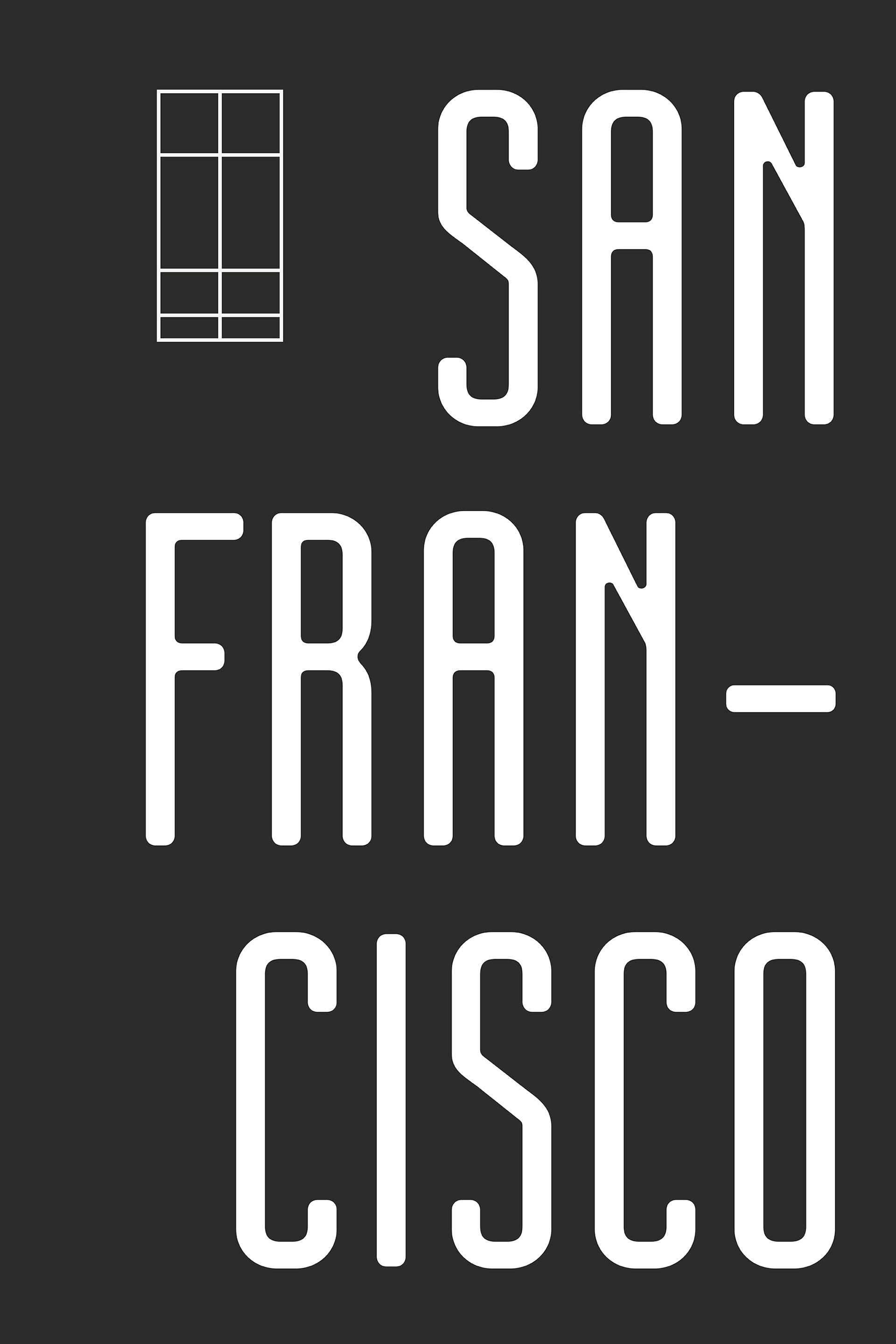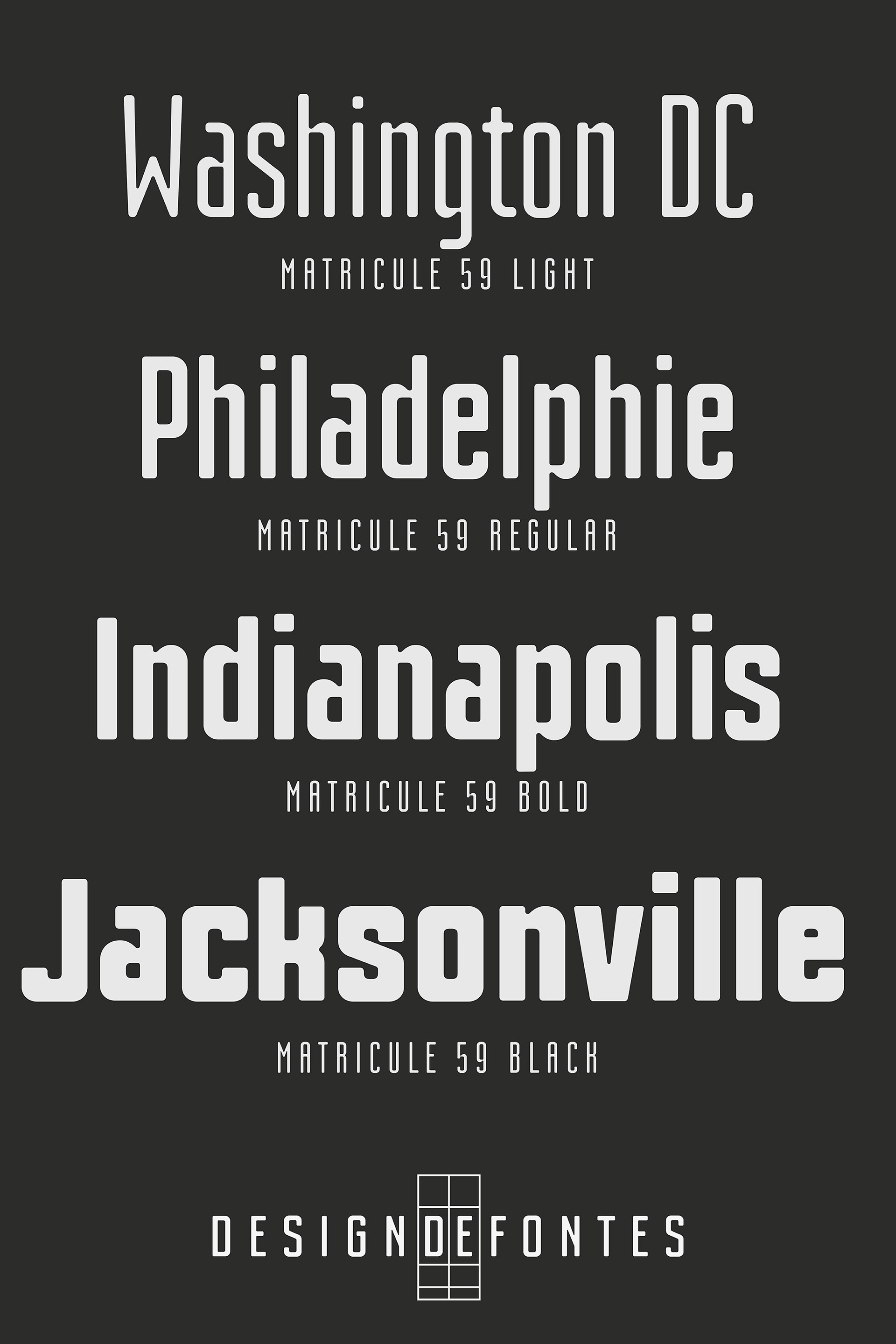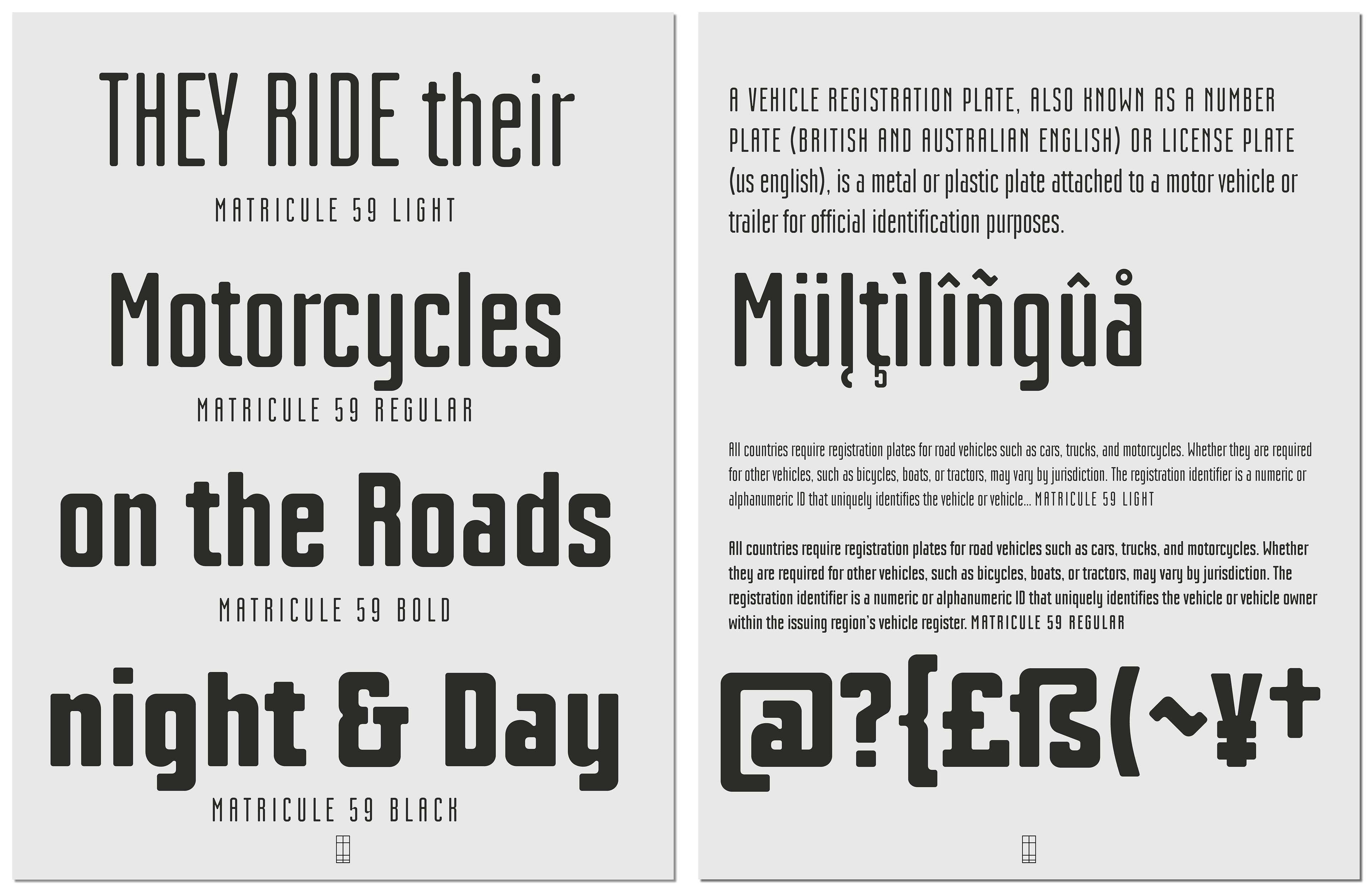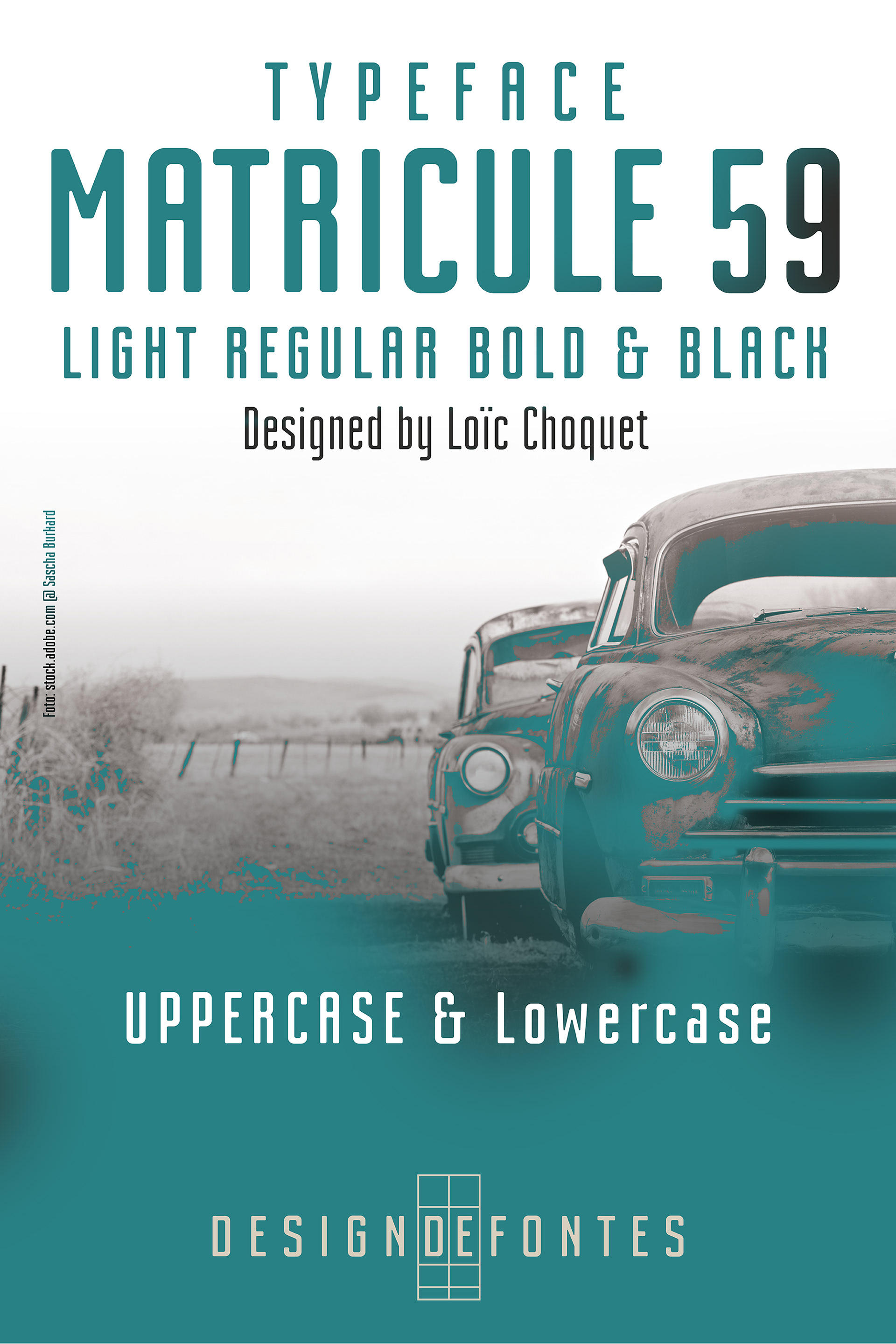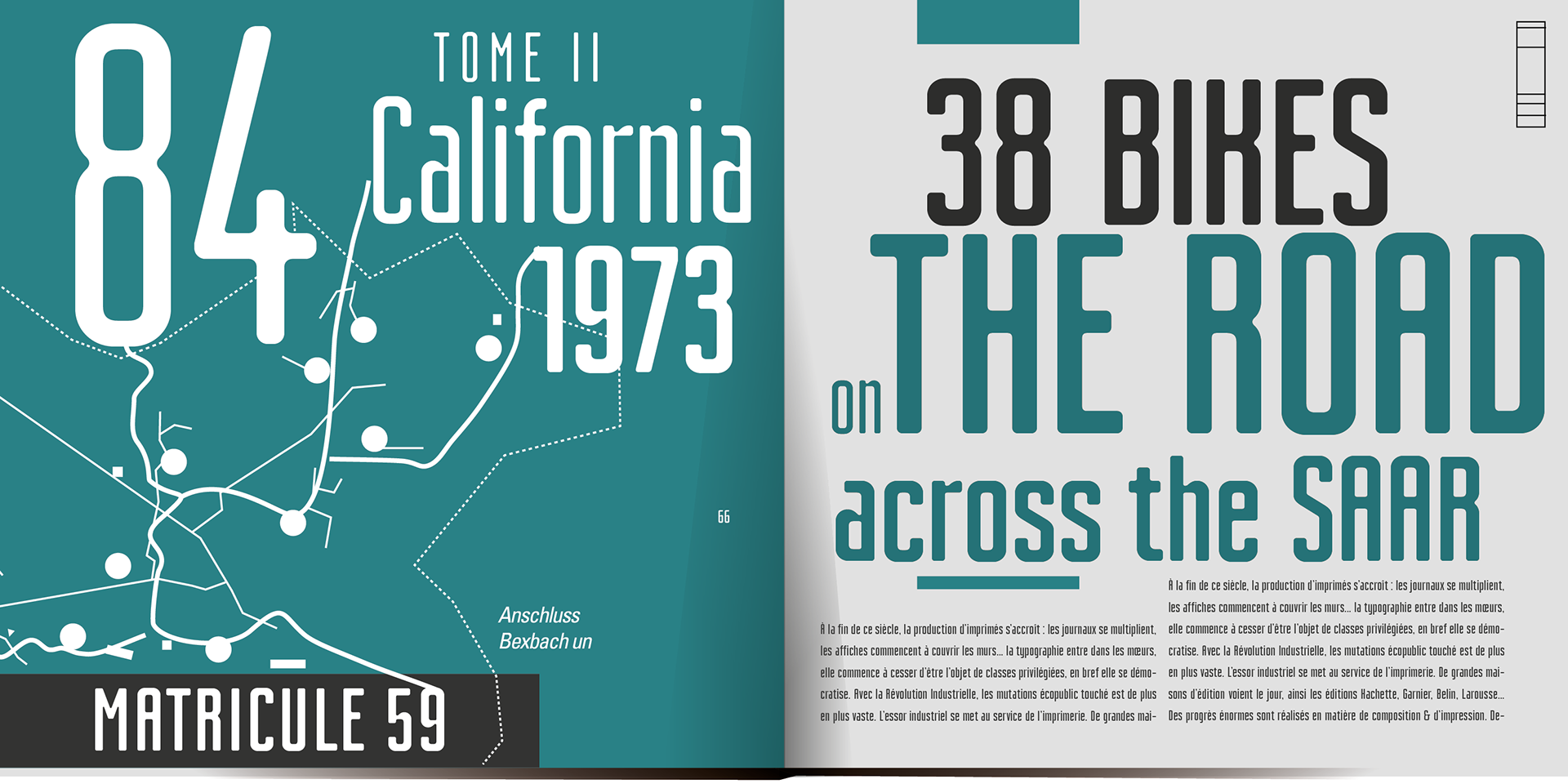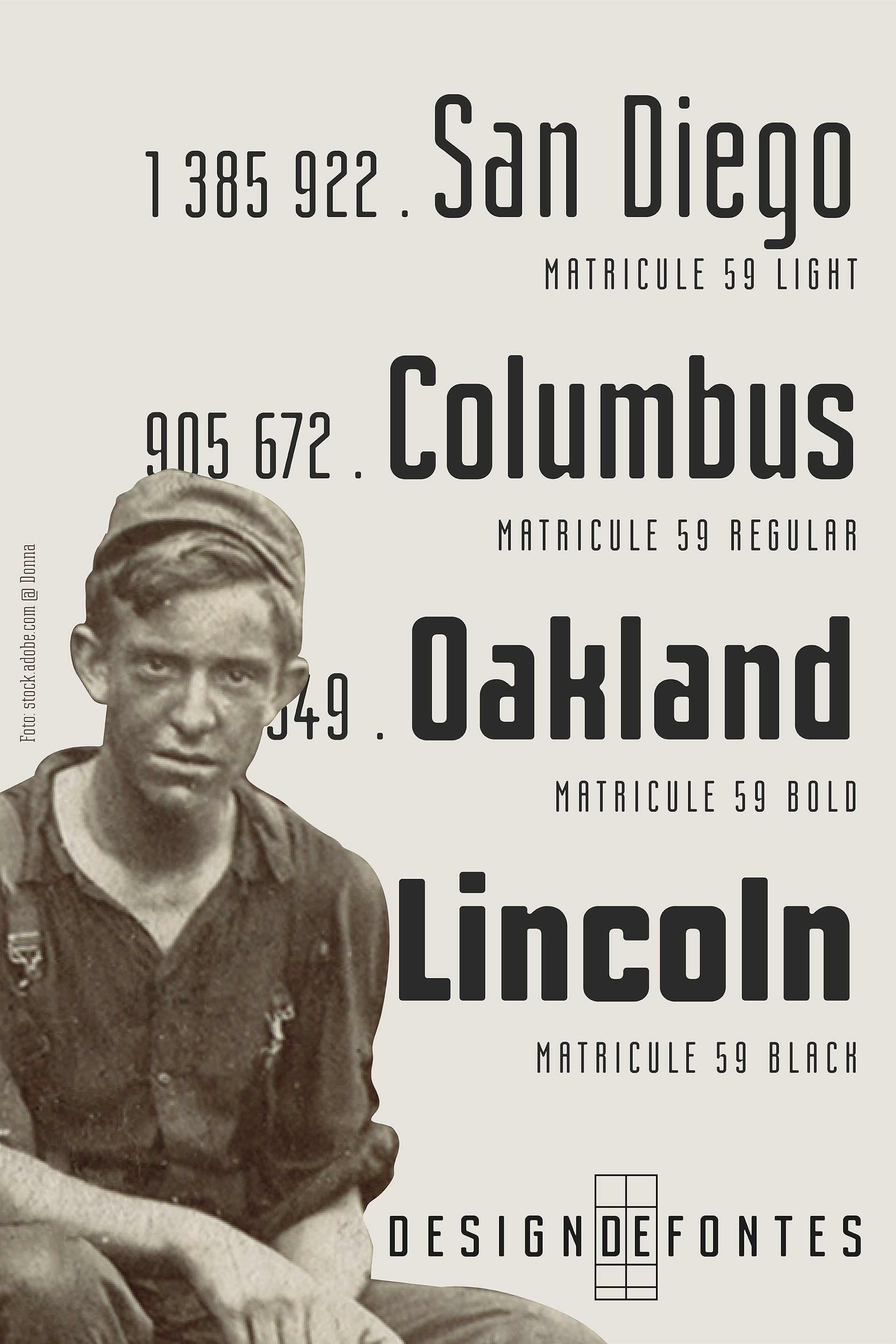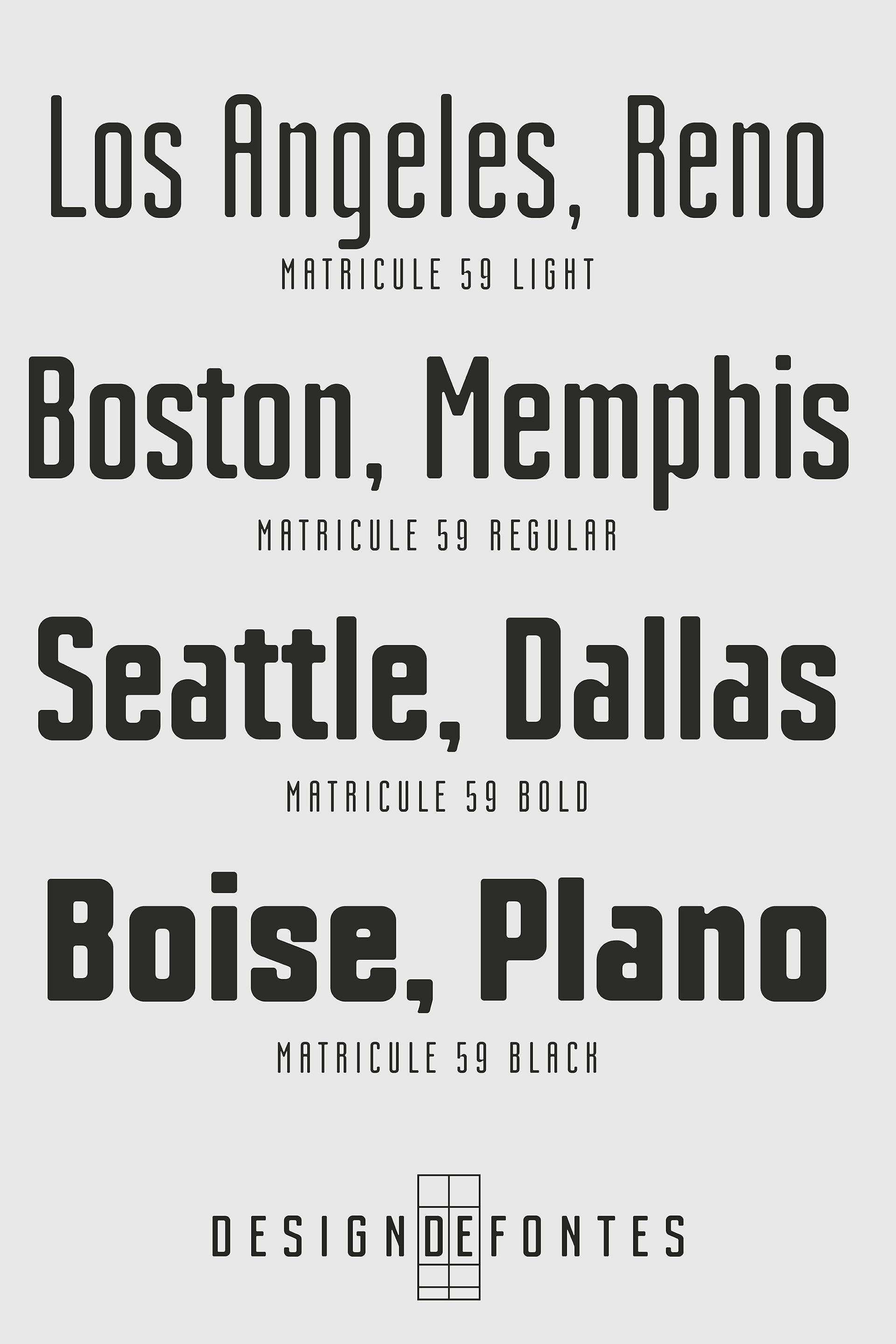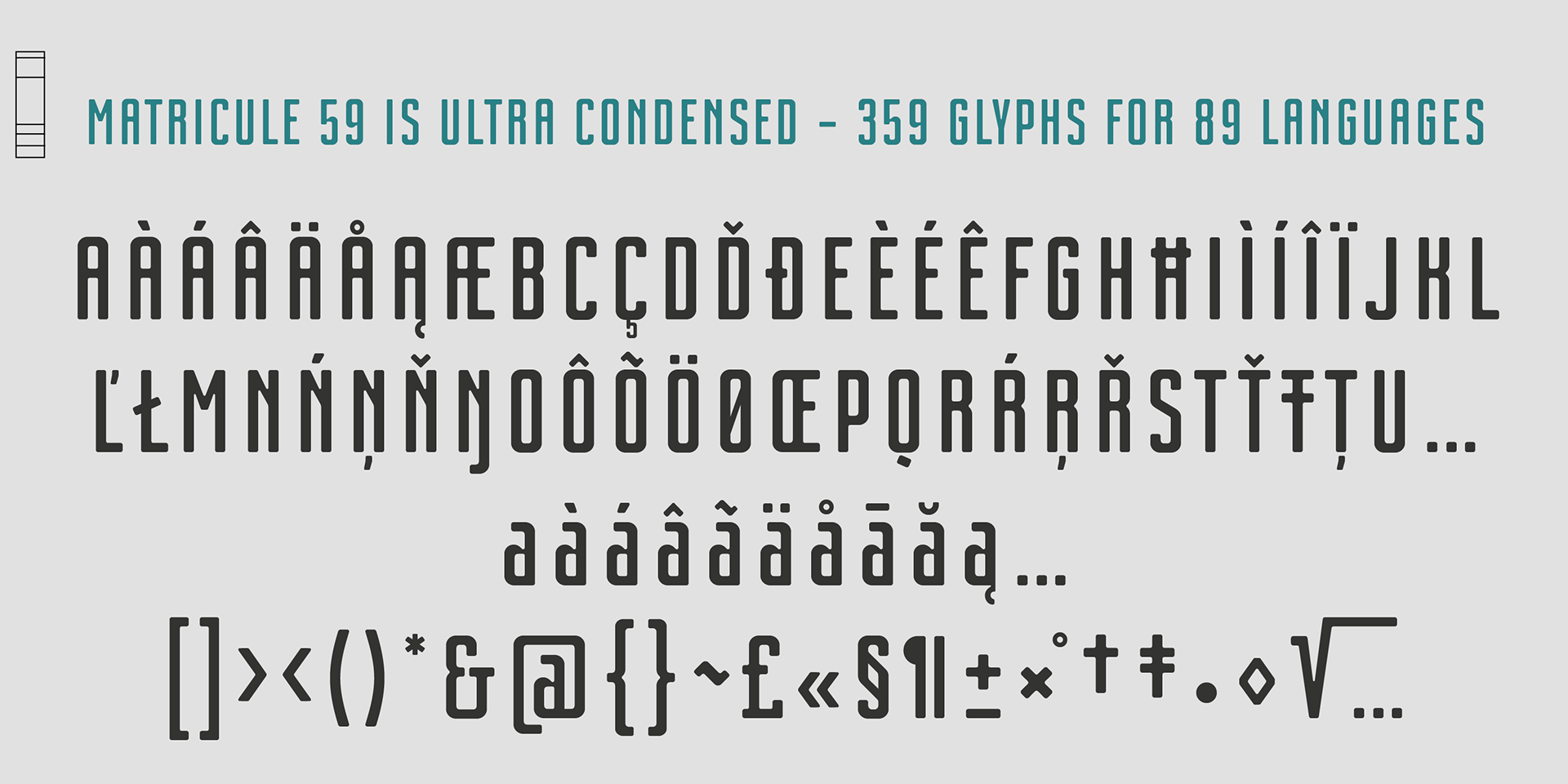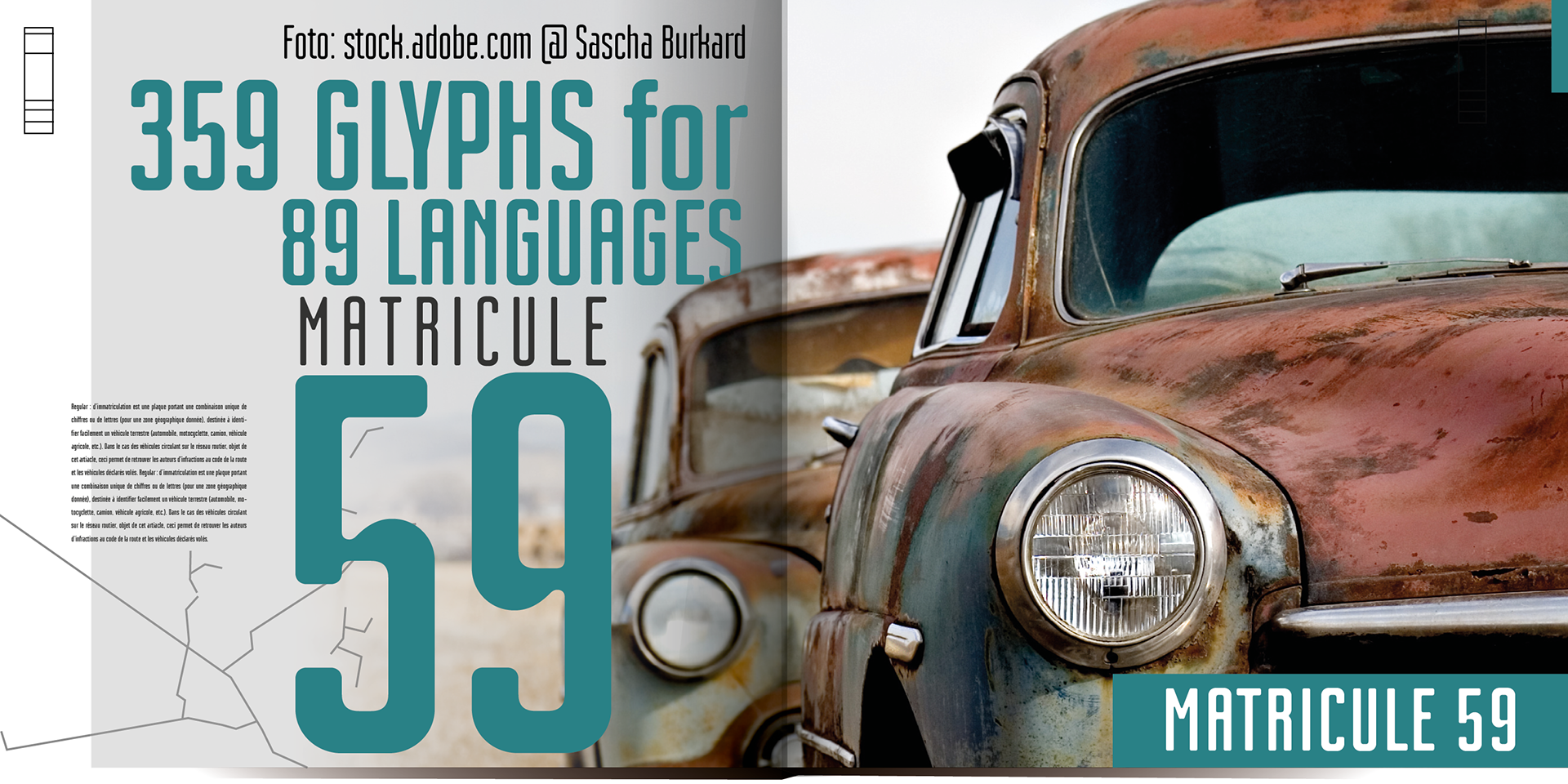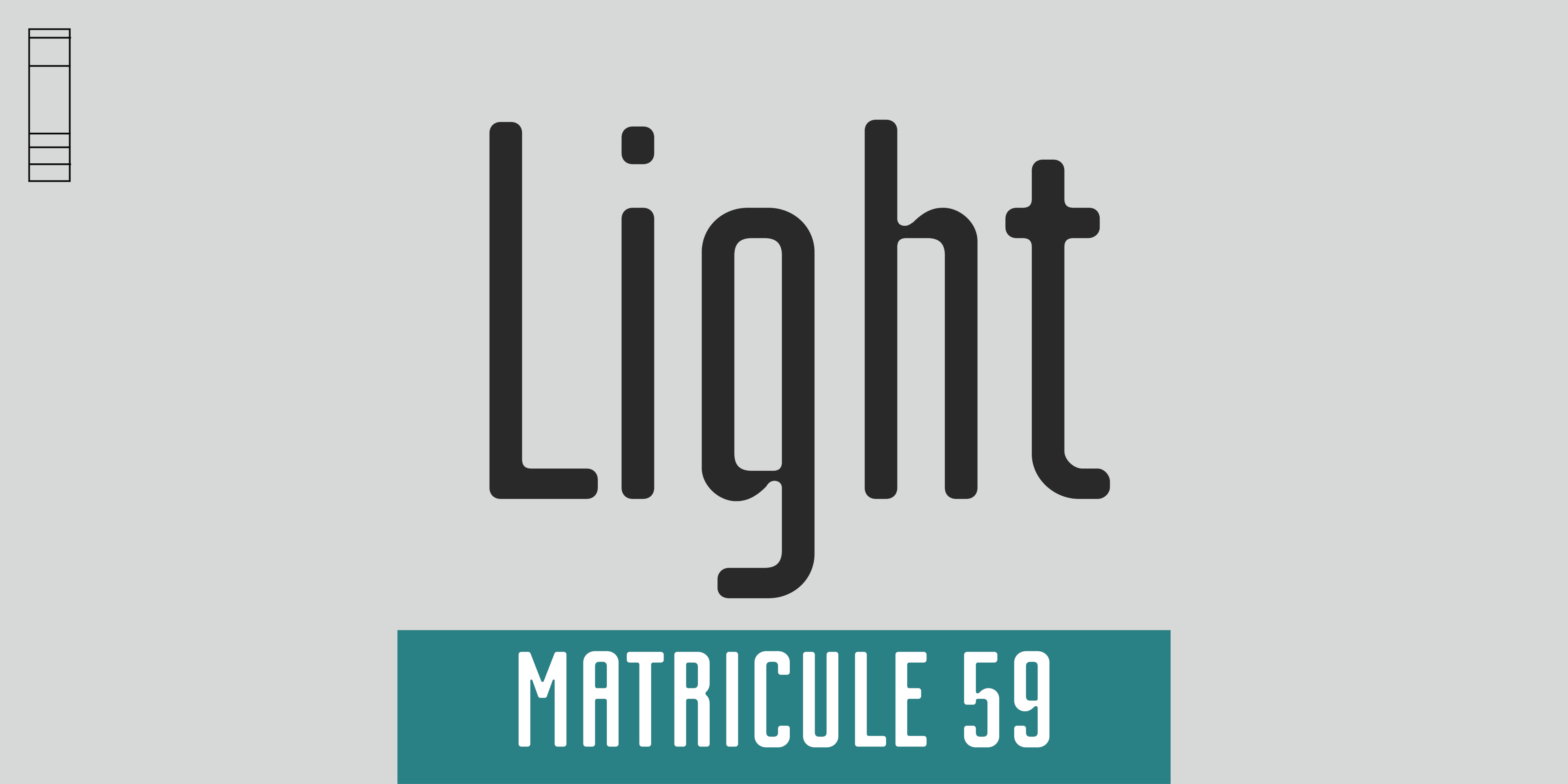
Matricule 59
Création de caractère typographique
(Loïc Choquet pour designdefontes, ma fonderie)
Typeface: Matricule 59
Matricule 59 est un caractère dont le design et inspiré par les plaques d’immatriculations et plus particulièrement par les déformations provoquées par la pression des caractères dans les plaques métalliques. Ces déformations donnent aux caractères un style spécifique notamment concernant les déliés de liaisons de ces caractères.
Matricule 59 est la version ultra condensée de Matricule, un caractère dessiné par Loïc Choquet.
4 STYLES (4 fontes) : Light, Regular, Bold and Black.
Chaque fonte contient 359 glyphes permettant ainsi l’emploi de ce caractère dans au moins 89 langues différentes